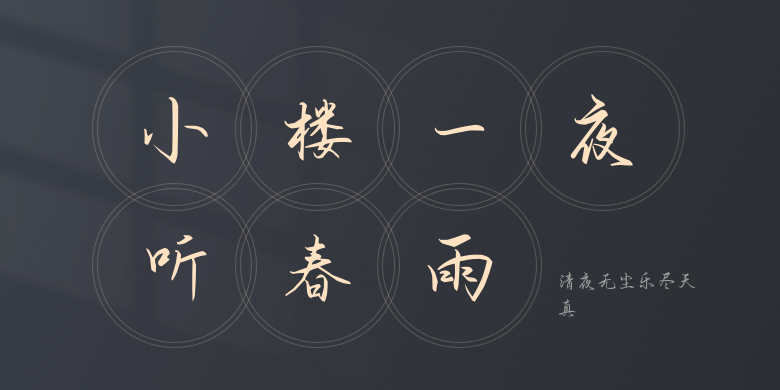
清夜无尘乐尽天真
清夜无尘乐尽天真,这款字体结构工整、笔画清晰,兼顾美观与易读性,适用于标题、正文、海报、包装、LOGO 等多种场景。字形优雅稳定,风格百搭耐看,适配日常排版与创意设计,让文字呈现更舒适、更具质感。清夜无尘乐尽天真一笔一画,皆是细节,以均衡的比例、流畅的线条打造舒适视觉体验,字形端正大气,风格简约现代。无论是商业设计、品牌宣传还是日常排版,都能轻松驾驭,让文字更有格调与力量。清夜无尘乐尽天真字体下载。